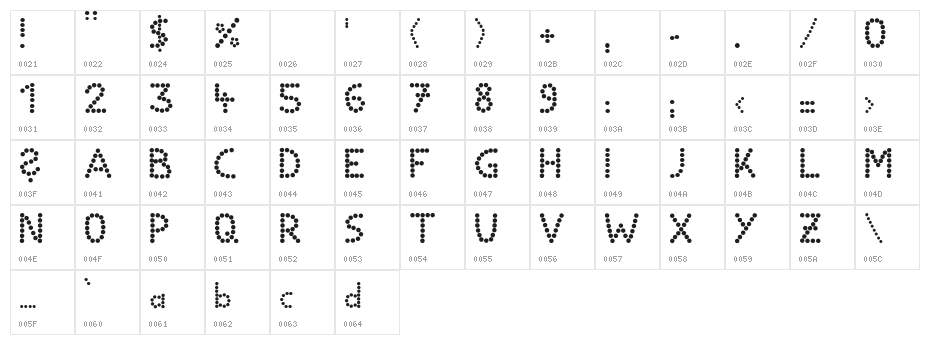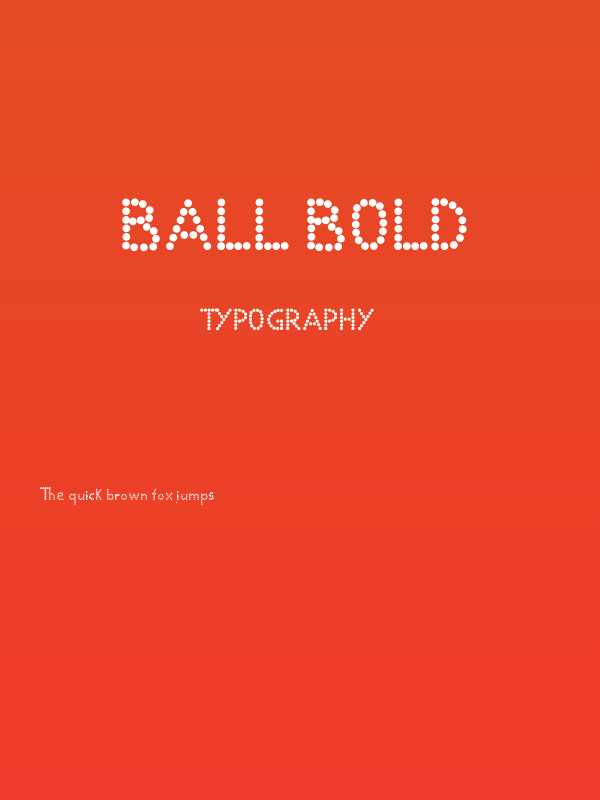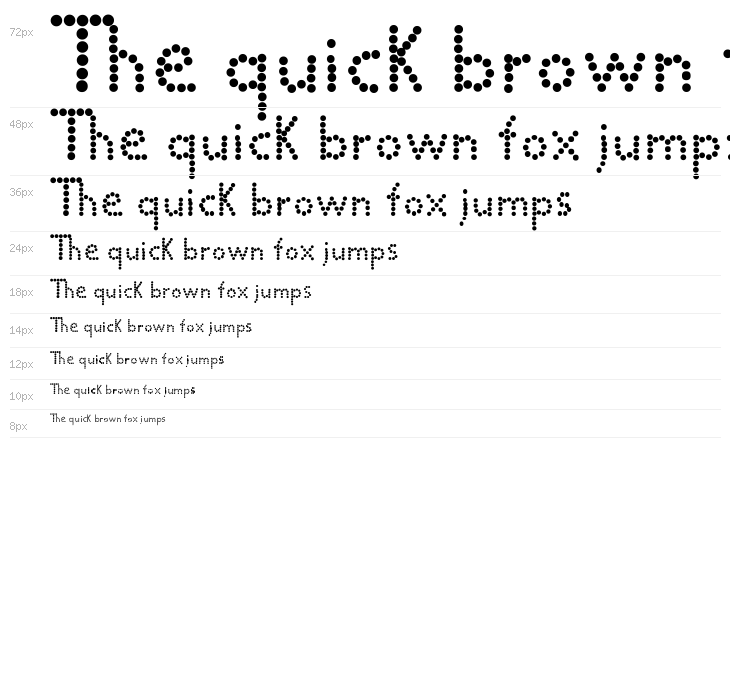
BALL bold Font
| Progetti proposti | Ideal for creative projects such as posters, logos, children's books, and party invitations where a fun and distinctive look is desired. |